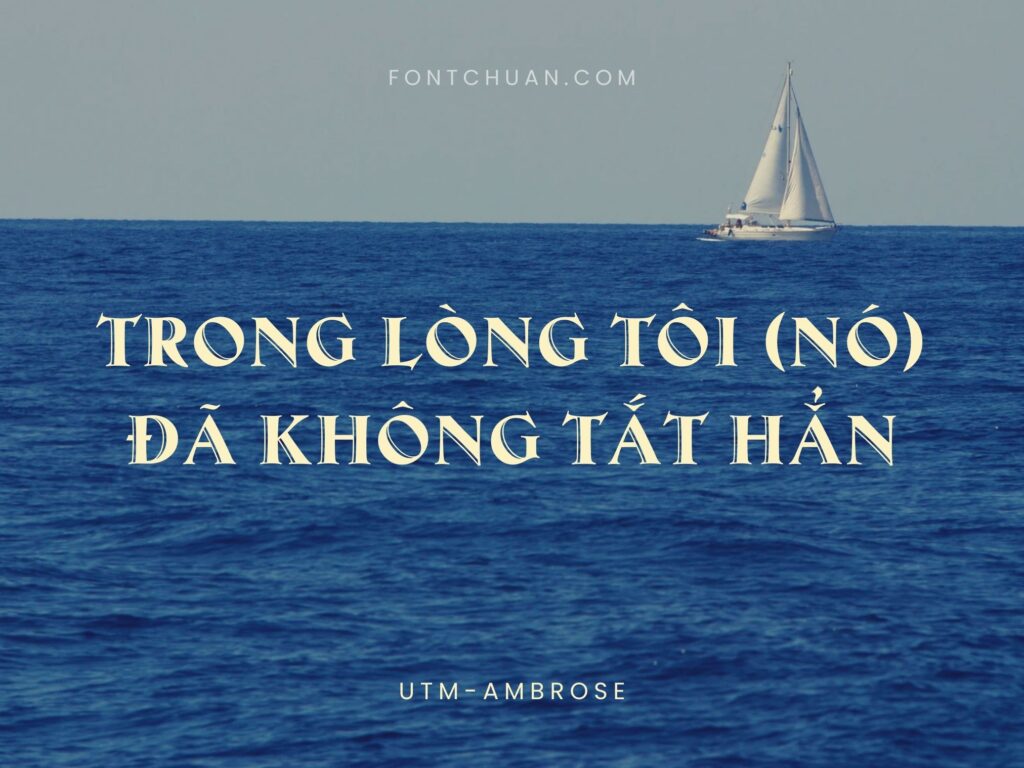
Font UTM Ambrose Việt Hóa
UTM Ambrose là một kiểu chữ serif mang phong cách cổ điển và thanh lịch, được phát triển bởi Công ty TNHH Vitoen. Thiết kế font này hướng đến sự chỉn chu, sang trọng và dễ ứng dụng trong nhiều loại hình thiết kế chuyên nghiệp. Font hỗ trợ đầy đủ tiếng Việt cùng hơn 200 ngôn ngữ khác, giúp mở rộng phạm vi sử dụng trên nhiều nền tảng khác nhau. Đây là một trong những kiểu chữ đã được thành viên Font Chuẩn sưu tầm và chọn lọc nhằm phục vụ cộng đồng sáng tạo, thiết kế và in ấn với yêu cầu cao về tính thẩm mỹ và độ tương thích đa ngôn ngữ.
UTM Ambrose có cấu trúc chữ chắc chắn, tỷ lệ cân đối, độ thanh đậm vừa phải cùng các chân chữ mềm mại đặc trưng của nhóm serif cổ điển. Font phù hợp cho các ứng dụng như thiết kế logo, tiêu đề sách báo, bìa tạp chí, bộ nhận diện thương hiệu hoặc các ấn phẩm in ấn trang trọng. Những ngành nghề như quảng cáo, giáo dục, bất động sản và công nghệ hoàn toàn có thể tận dụng Ambrose để tạo nên sự tinh tế, rõ ràng và đáng tin cậy trong mọi thiết kế.